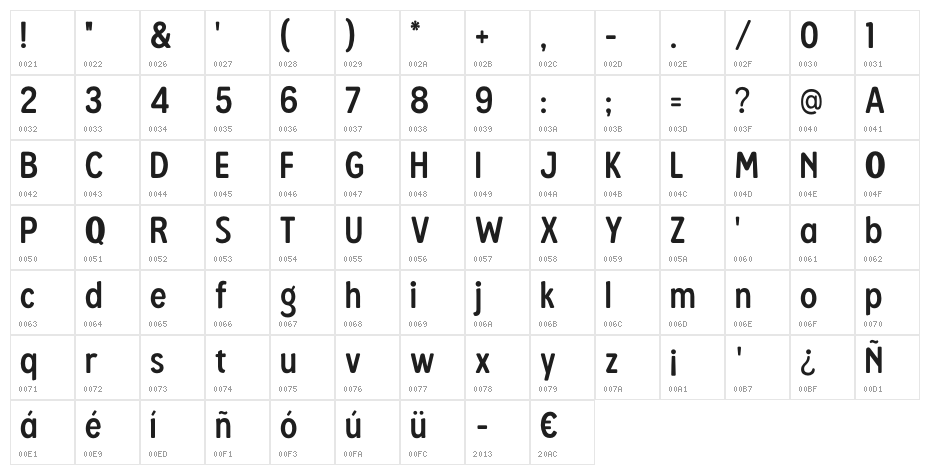
Mousse Font
| العرض | Condensed |
| حالة الاستخدام | Headlines, Logos, Branding |
| مشاريع مقترحة | Ideal for branding, advertising, packaging, and children's books due to its playful yet professional appearance. |